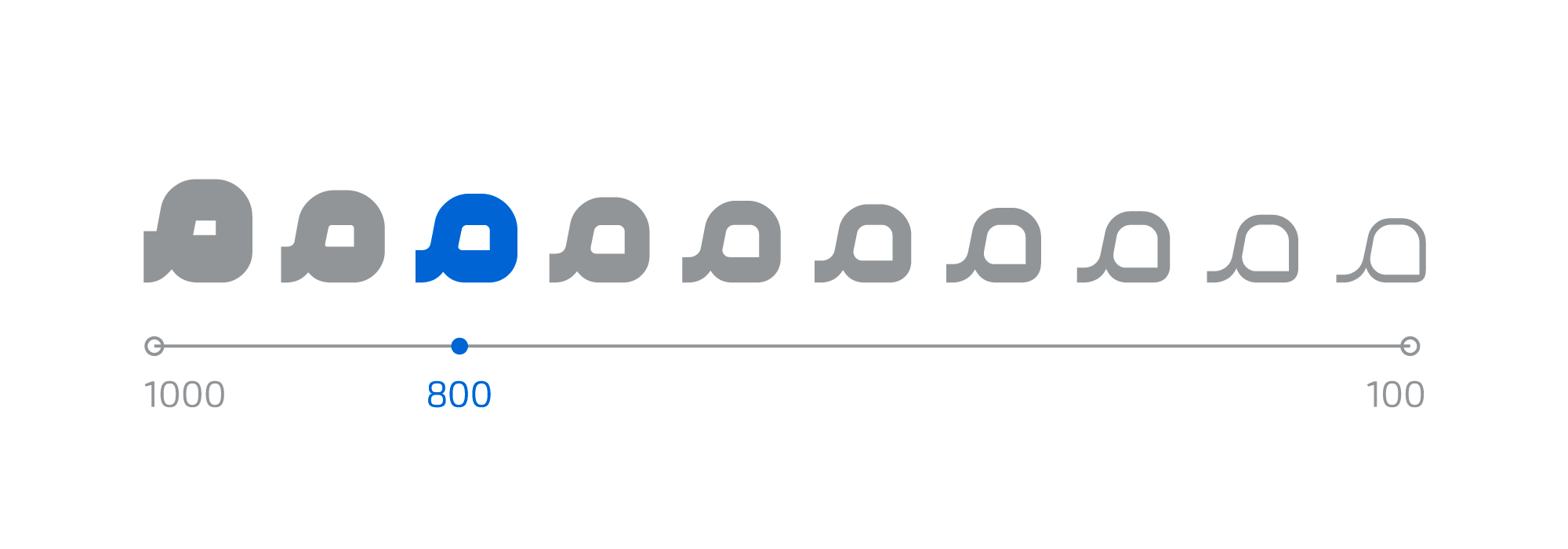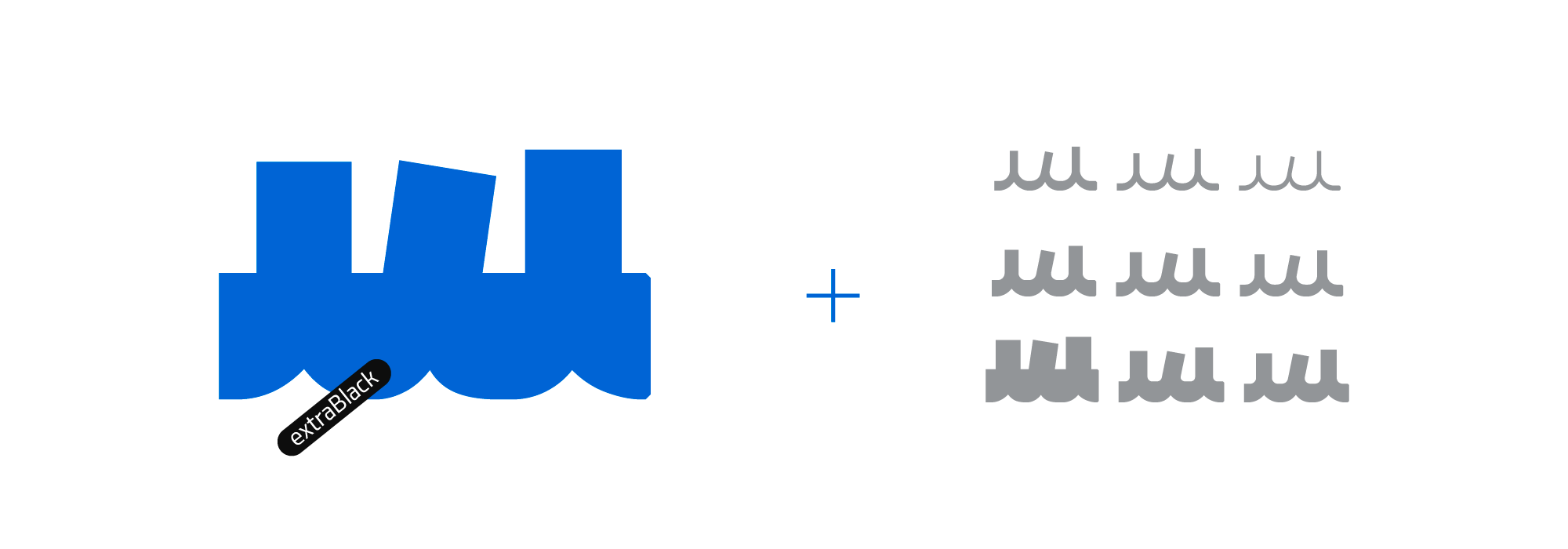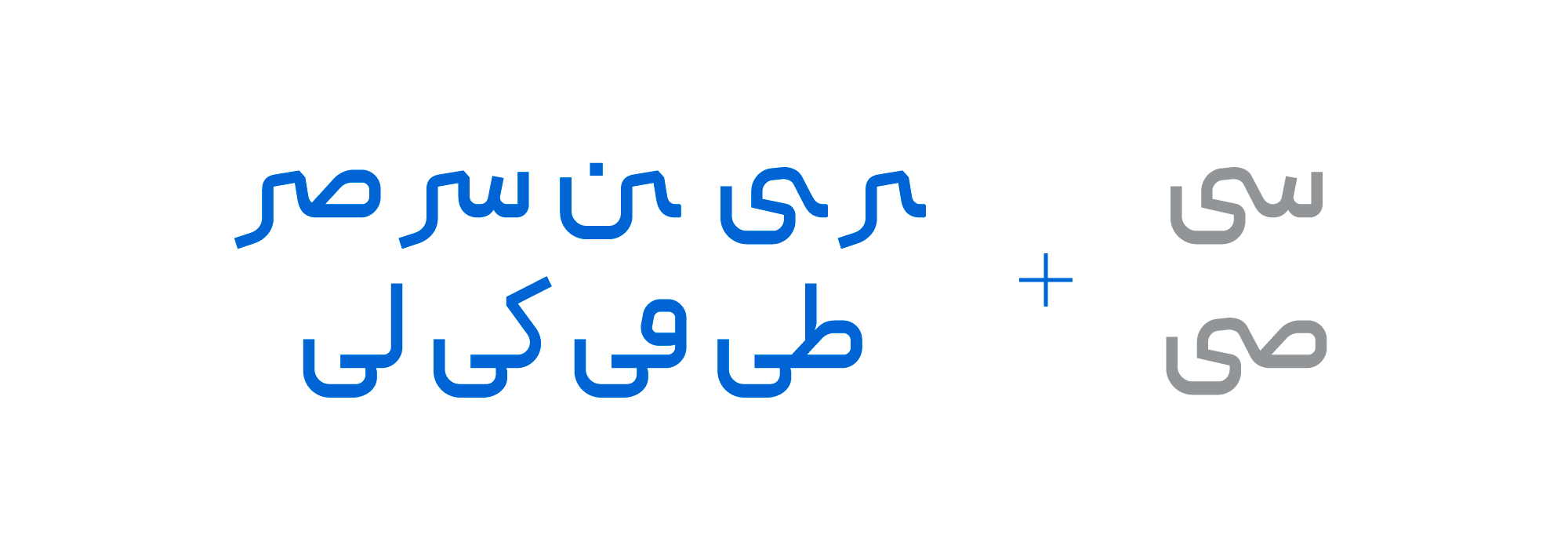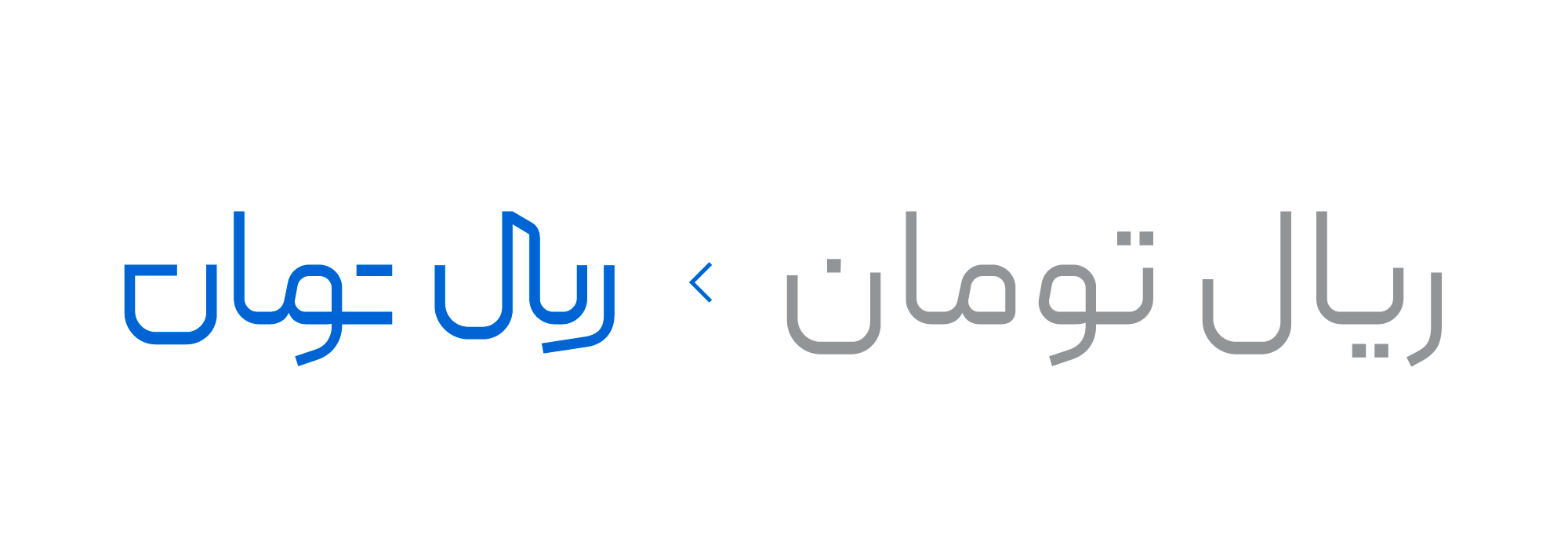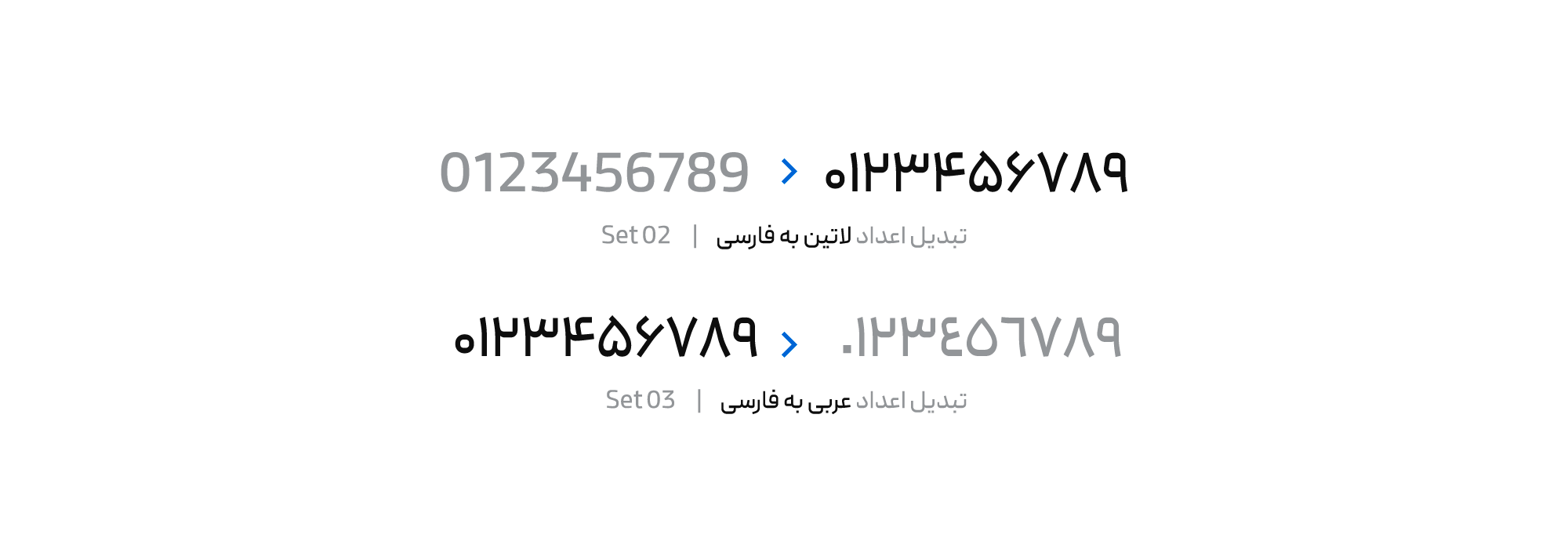
در چهارمین نسخه فونت پیدا چه تغییراتی میبینیم؟
در نسخه چهارم علاوه بر رفع برخی ایرادات فنی و طراحی، ویژگیهایی به فونت اضافه شده است.
۱. اضافه شدن نسخه وریبلفونت
۲. اضافه شدن وزن اکسترابلک
۳. اضافه شدن لیگیچرهای جدید
۴. طراحی لیگیچرهای ریال و تومان
۵. اضافه شدن امکان فارسیسازی اعداد با استفاده از تنظیمات فونت فیچر ستینگ در Css
۶. اصلاح فرم بعضی از حروف و تنظیم فاصلهی حروف در زبان لاتین
۷. تغییر دستهبندی کاف و گاف کشیده از Stylistic Set به Swash
۸. پشتیبانی کاملتر از زبانهای اردو و کوردی